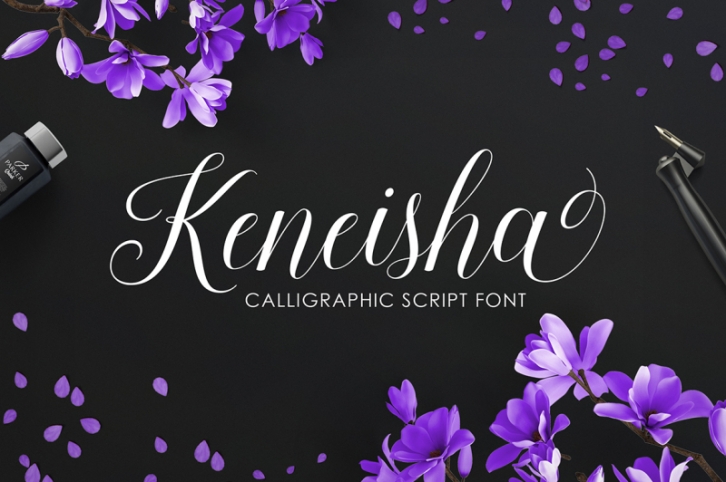
Keneisha adalah font naskah kaligrafi dengan baseline yang bervariasi, yang dirancang untuk menyampaikan keanggunan dan gaya. Ini adalah garis halus, bersih dan feminin. Bekerja dengan sempurna untuk logo, majalah, menu, buku, undangan, kartu ucapan / pernikahan, pengemasan, label, kaos dll. Semua desain Anda akan memiliki sentuhan buatan sendiri yang indah dengan Keneisha.
Keneisha menampilkan 341+ glyph dan 157 karakter alternatif. termasuk huruf awal dan terminal, alternatif, ligatur dan dukungan beberapa bahasa.